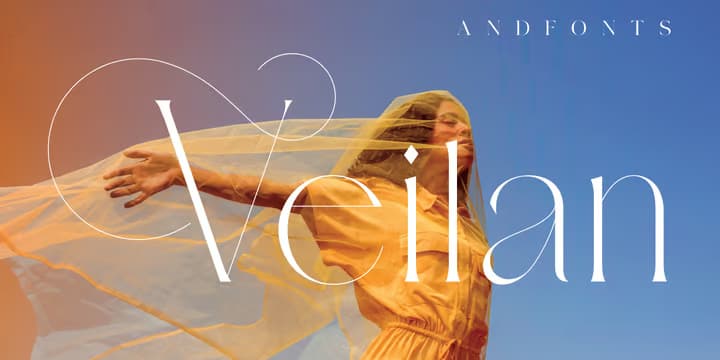
Veilan
繊細でシックなディスプレイローマン。基本はヘアラインが特徴的なややコントラストのあるエレガントなグリフで、大文字には見ての通り非常に繊細なスワッシュが付いている。グリフはちょっと変わったところはあるがそれほど変形しておらずほぼスタンダード。大文字と小文字のサイズ差が大きい Extra というタイプもあり、大文字を目立たせたい場合はこちらを使うといいだろう。それぞれにスモールキャップスタイプもある。